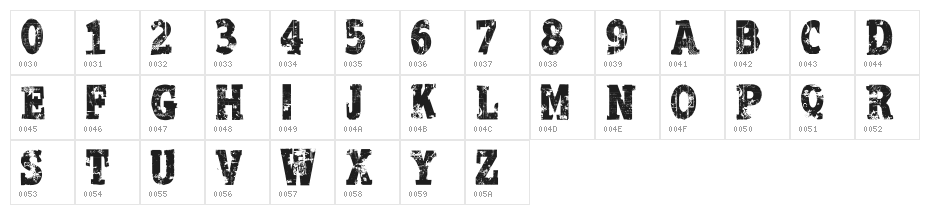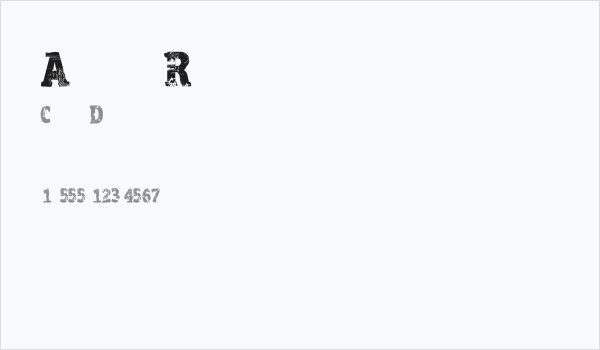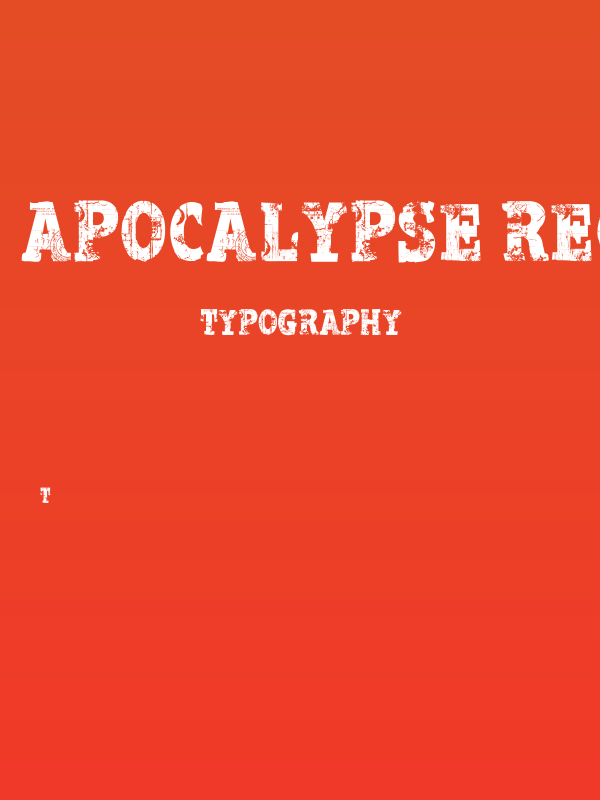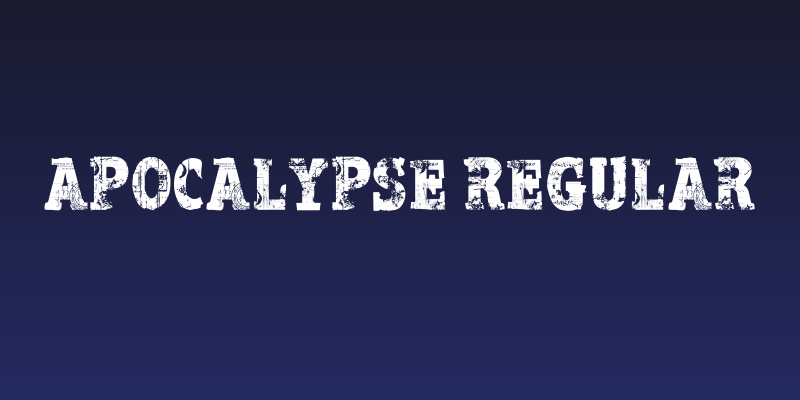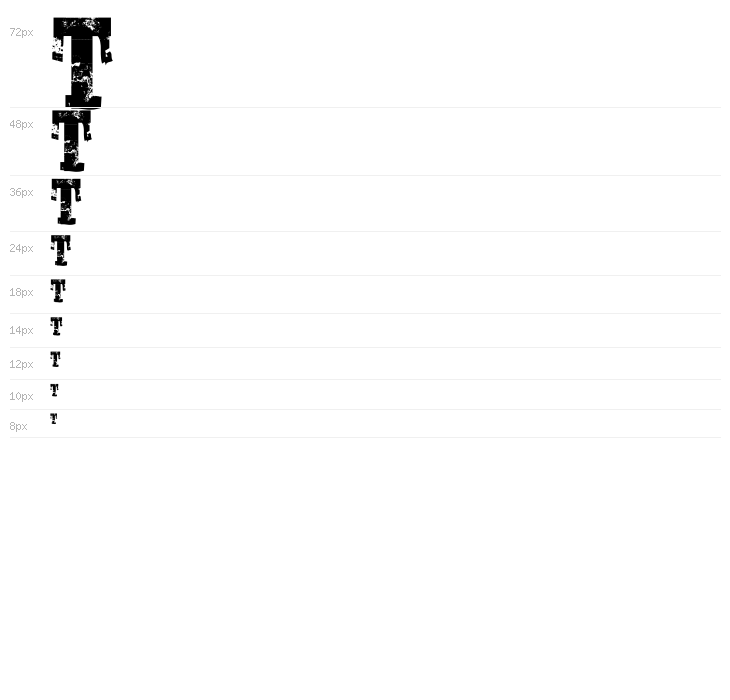
Apocalypse Regular Font
| おすすめプロジェクト | Ideal for use in posters, album covers, video game graphics, and any project needing a strong, edgy aesthetic. |